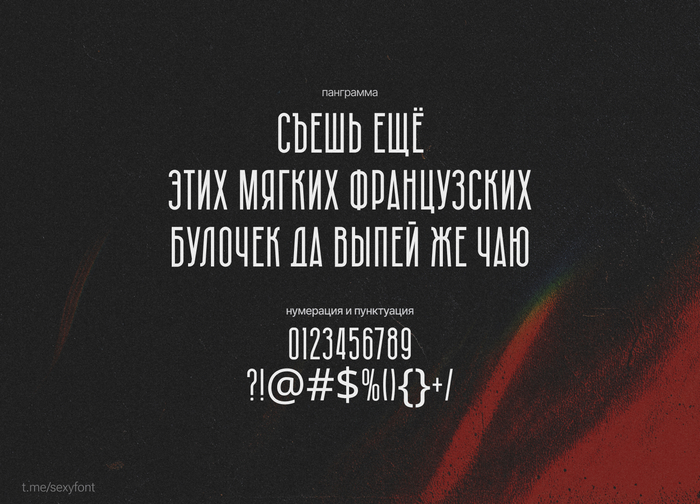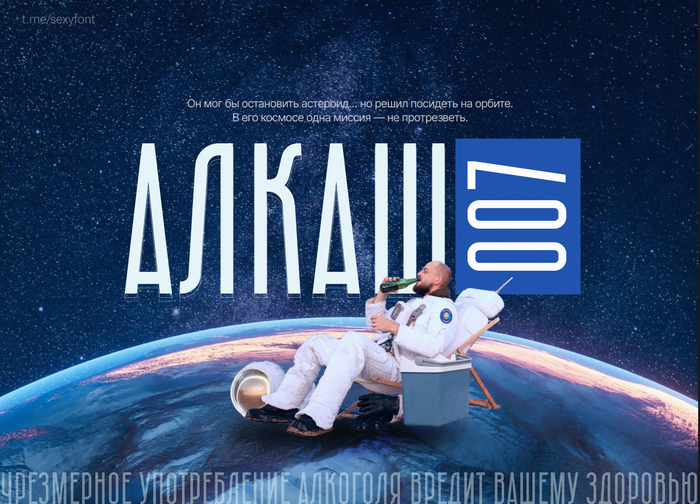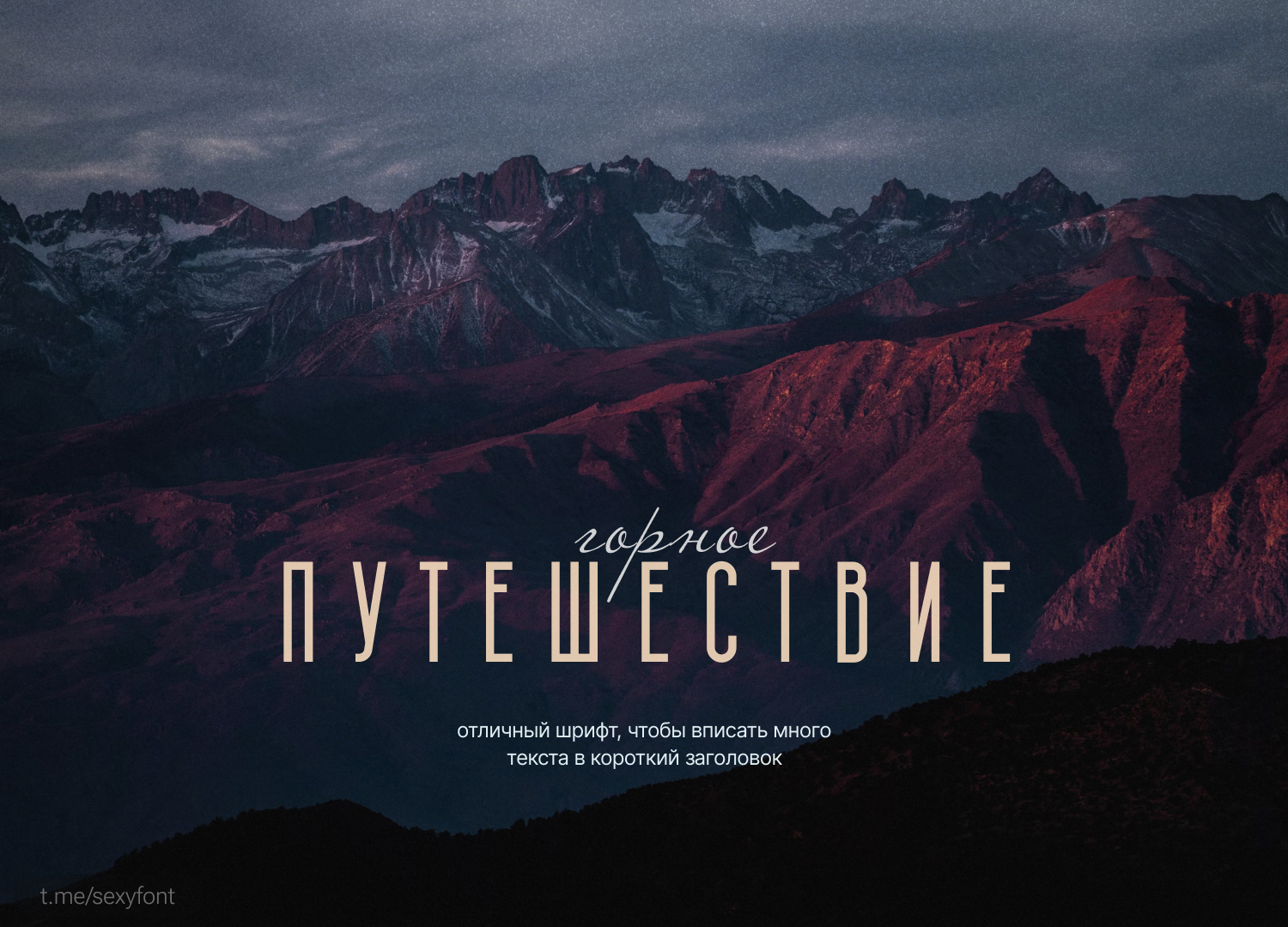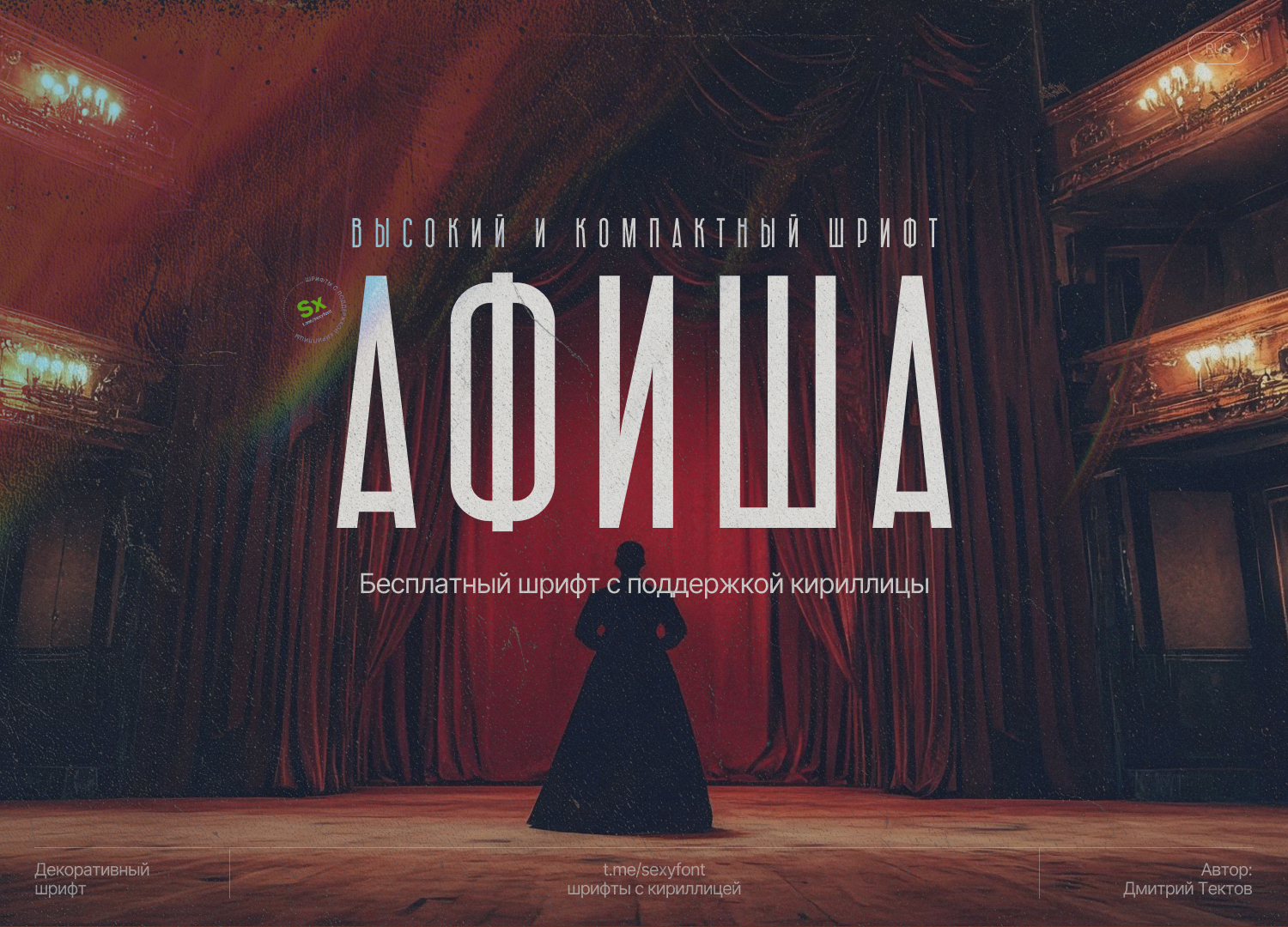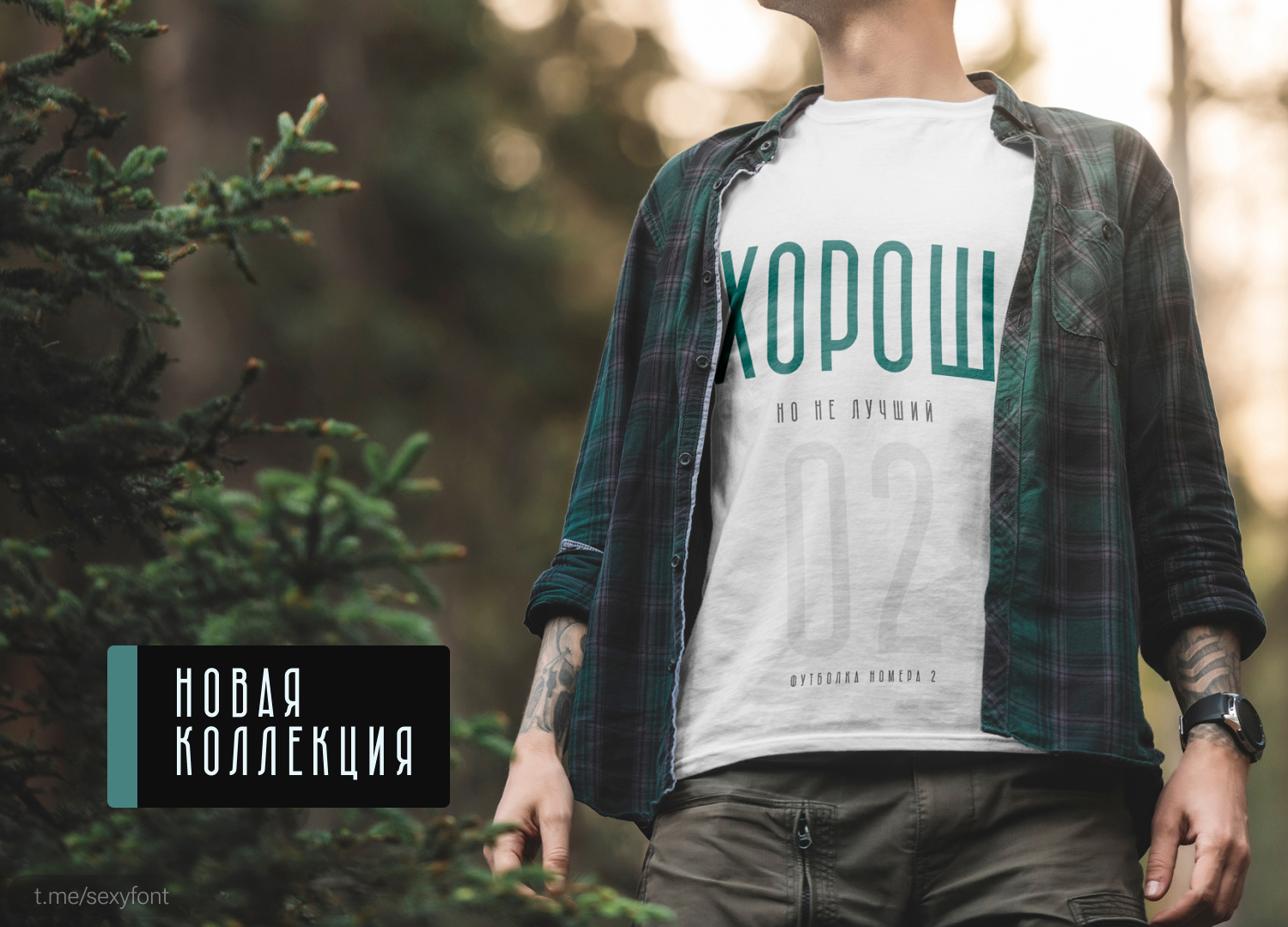
Бесплатный шрифт Афиша (TD Afisha)
Доделал новую презентацию) Еще один классный шрифт от Дмитрия. Это высокий и компактный шрифт, идеально для заголовков, когда маловато места. Вполне читаемых для небольших объемов текста.